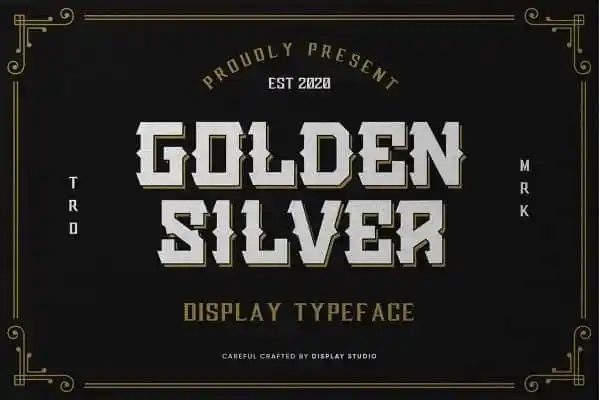
Golden Silver Display Font – Download Grátis
Esta é uma fonte display chamada Golden Silver Display Font, projetada por um estúdio chamado Display Studio para uma plataforma de design online conhecida como 99designs. Inspirada nos designs vintage, esta fonte oferece linhas limpas e suaves, com um toque moderno que combina perfeitamente em ambientes onde deseja destacar sua presença elegante e clássica. Com suas linhas finas e sólidas contrastando harmoniosamente, Golden Silver Display Font é ideal para criar uma marca distintiva em elementos de design como grafismos, logotipos e títulos. Seja você criador visual ou designer web, esta fonte pode ajudar a destacar seu trabalho, proporcionando um toque único que cativará os olhos do público.